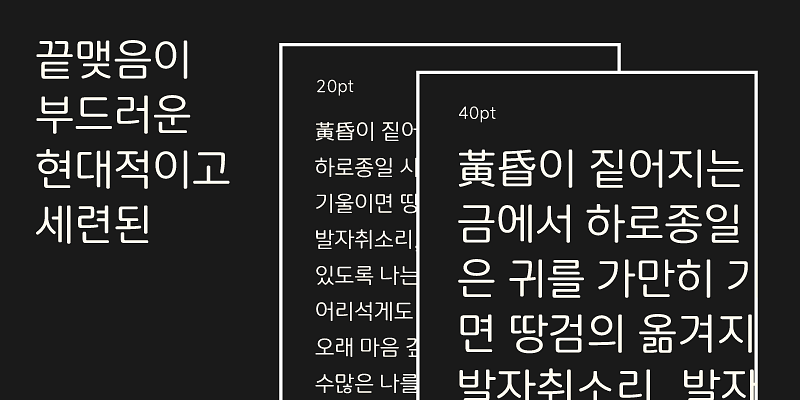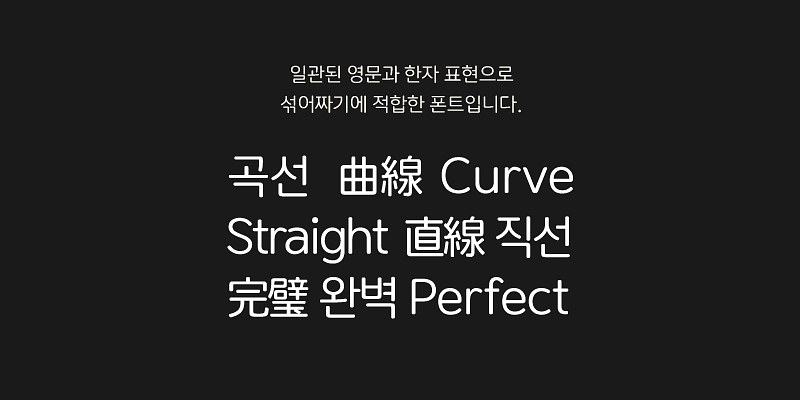
글꼴 페어링 가이드를 통해 자세한 내용 확인 >윤굴림700은 구조적인 완성도를 높여 조형적으로 아름답게 구축한 최고의 굴림체입니다. 제목부터 본문까지 제약없이 사용할 수 있도록 710부터 790까지 9단계의 굵기로 제작되었으며 그중 750은 가장 대중적으로 사용되는 굵기입니다.
영문과 한자까지 일관된 디자인으로 섞어짜기에 적합하며 곡선과 직선의 황금비율로 안정이면서 현대적이고 세련된 굴림체를 완성하였습니다.